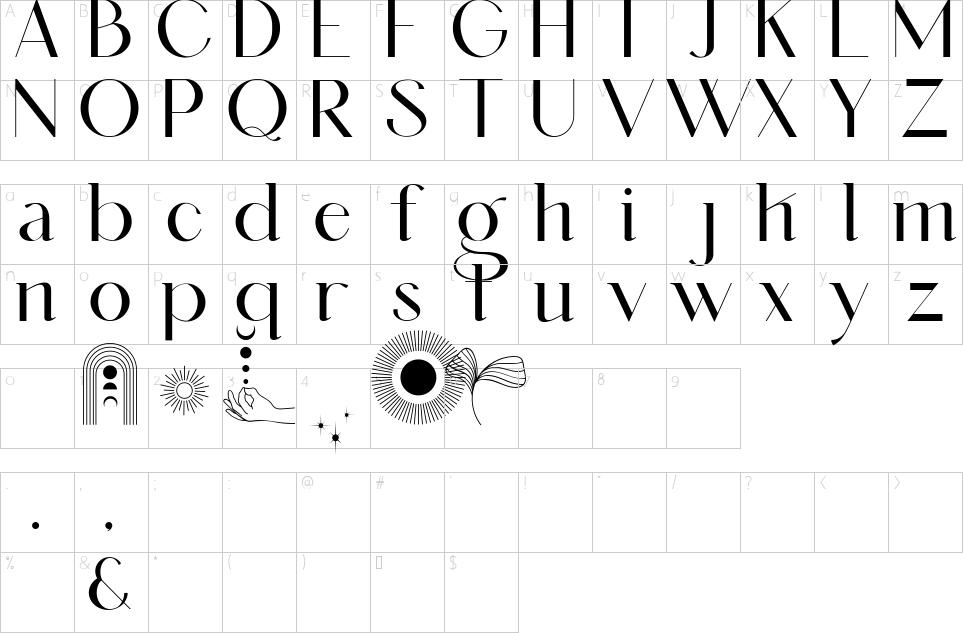
A fonte Amelaryas é um presente para designers e criativos que desejam adicionar um toque único à suas criações digitais. Desenhada pelo designer brasileiro putu dody permana, a Amelaryas oferece um design elegante e versátil, adequado para diversos tipos de projetos, desde designs gráficos até layout web. Com um design limpo e moderno, a Amelaryas ajuda a destacar seu trabalho ao fornecer um estilo distintivo. Desenvolvida para quem valoriza um design minimalista e de alta qualidade, a Amelaryas vem em versões para sistemas Windows e Mac, permitindo que ela seja facilmente integrada em qualquer projeto digital. Como uma fonte gratuita e de qualidade, Amelaryas é uma excelente escolha para designers que buscam recursos de alta qualidade sem se preocuparem com custos. Desde que foi disponibilizada, a fonte Amelaryas já foi baixada mais de 241 vezes, testemunhando seu valor e popularidade entre designers brasileiros e do mundo todo.